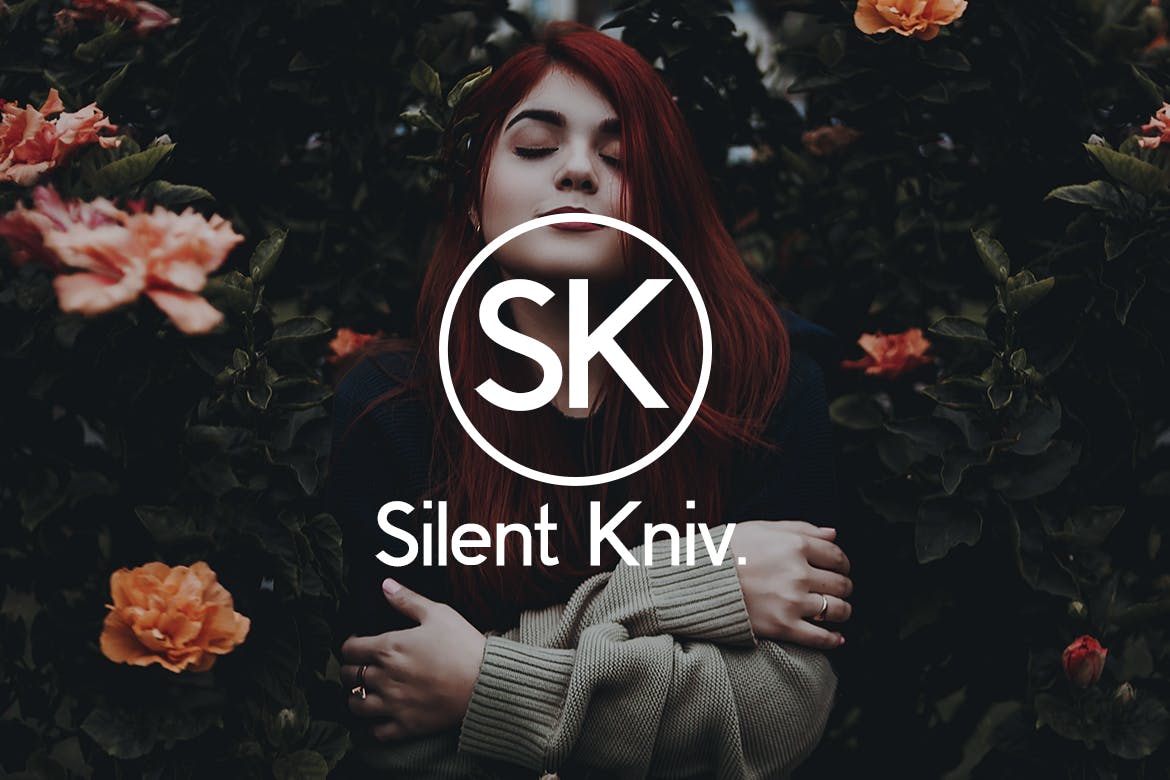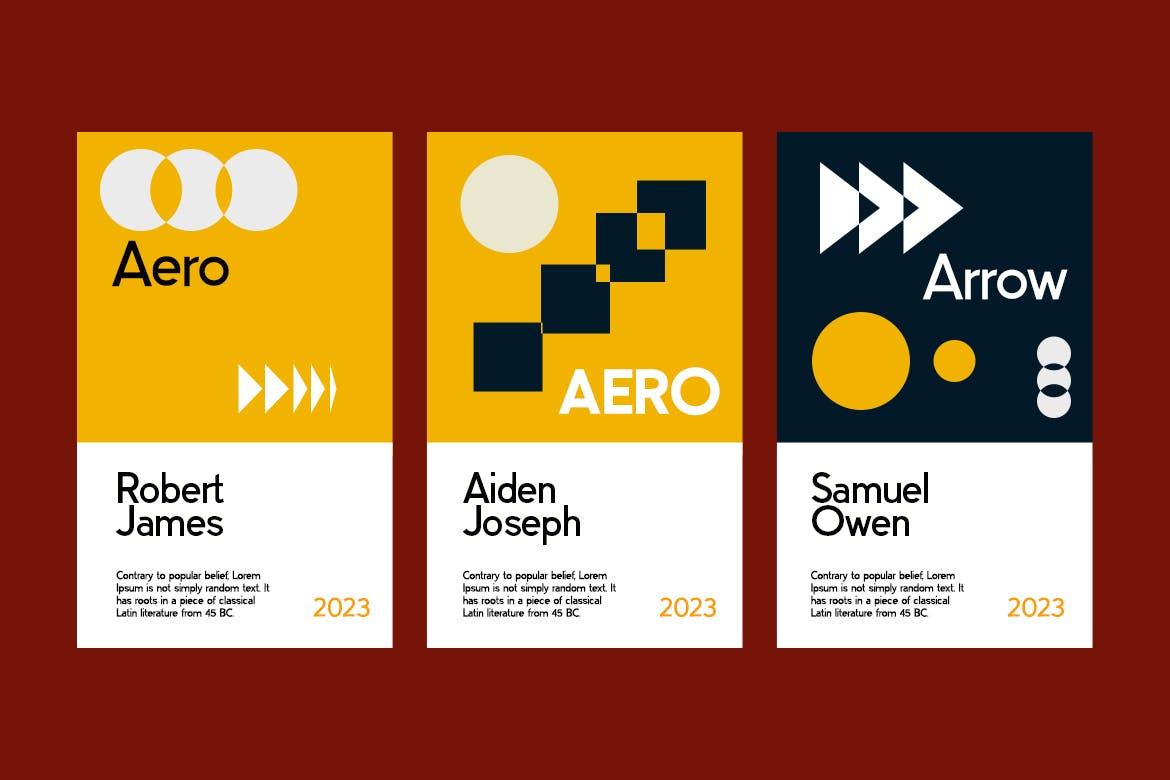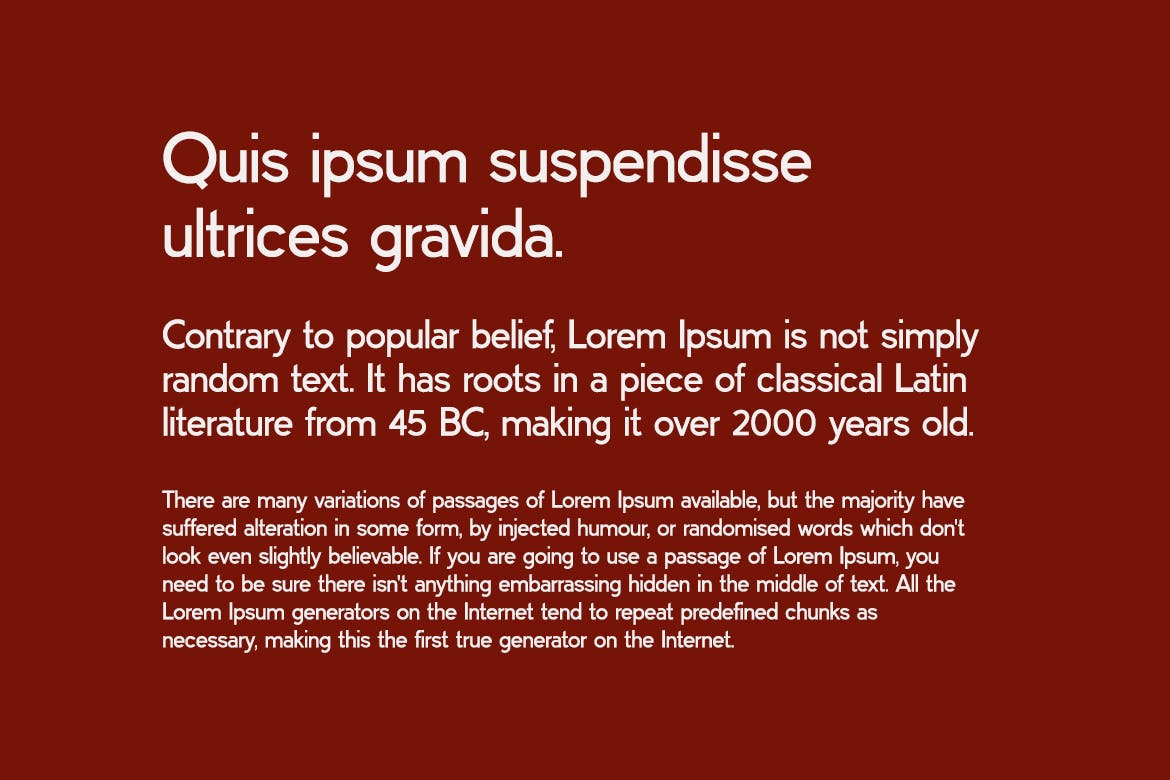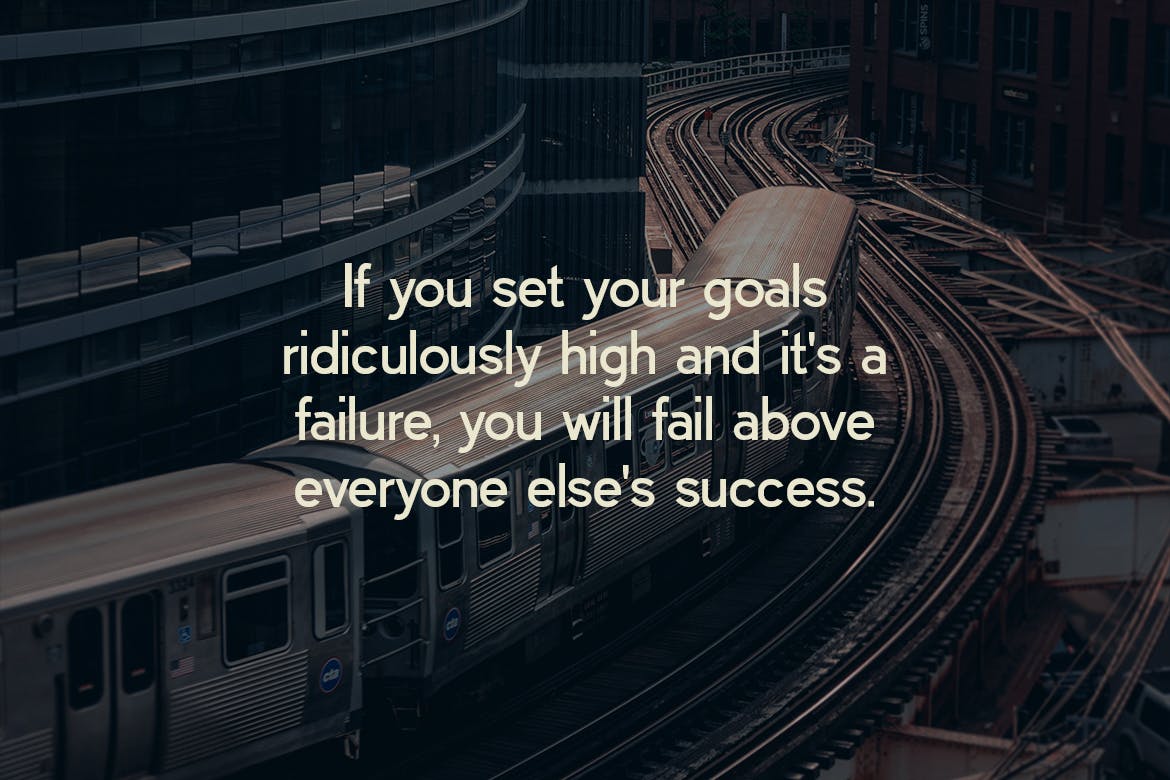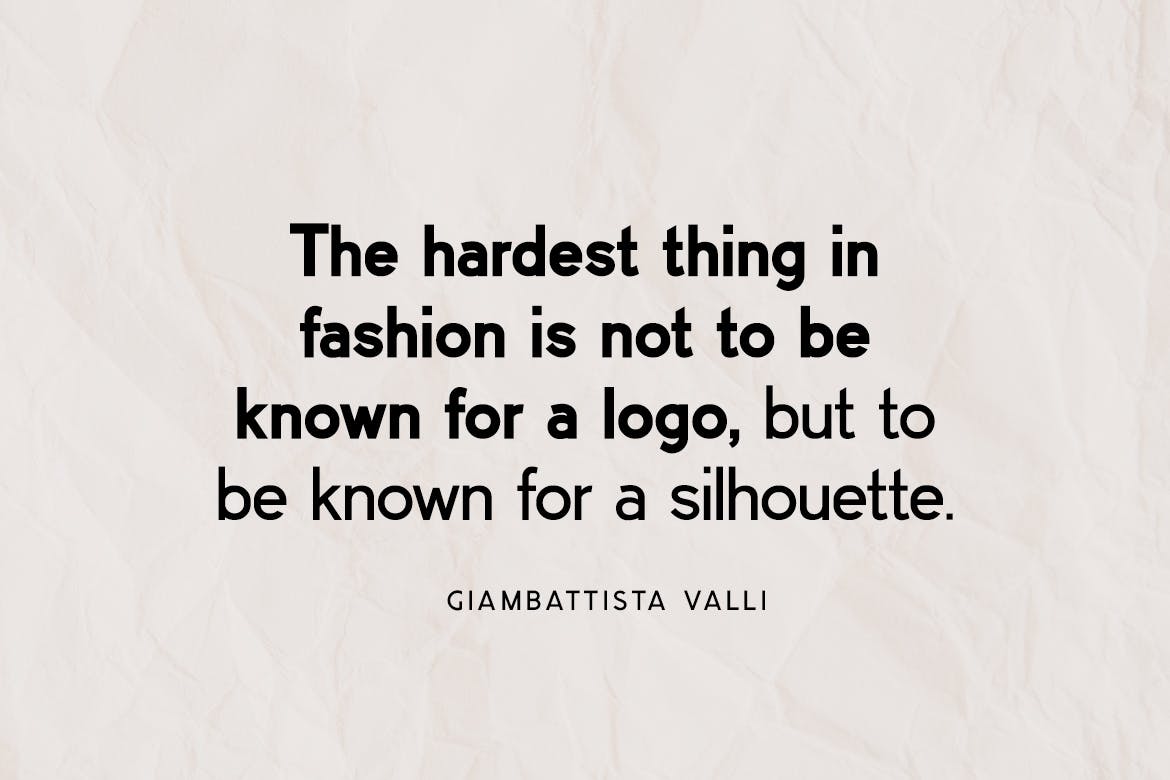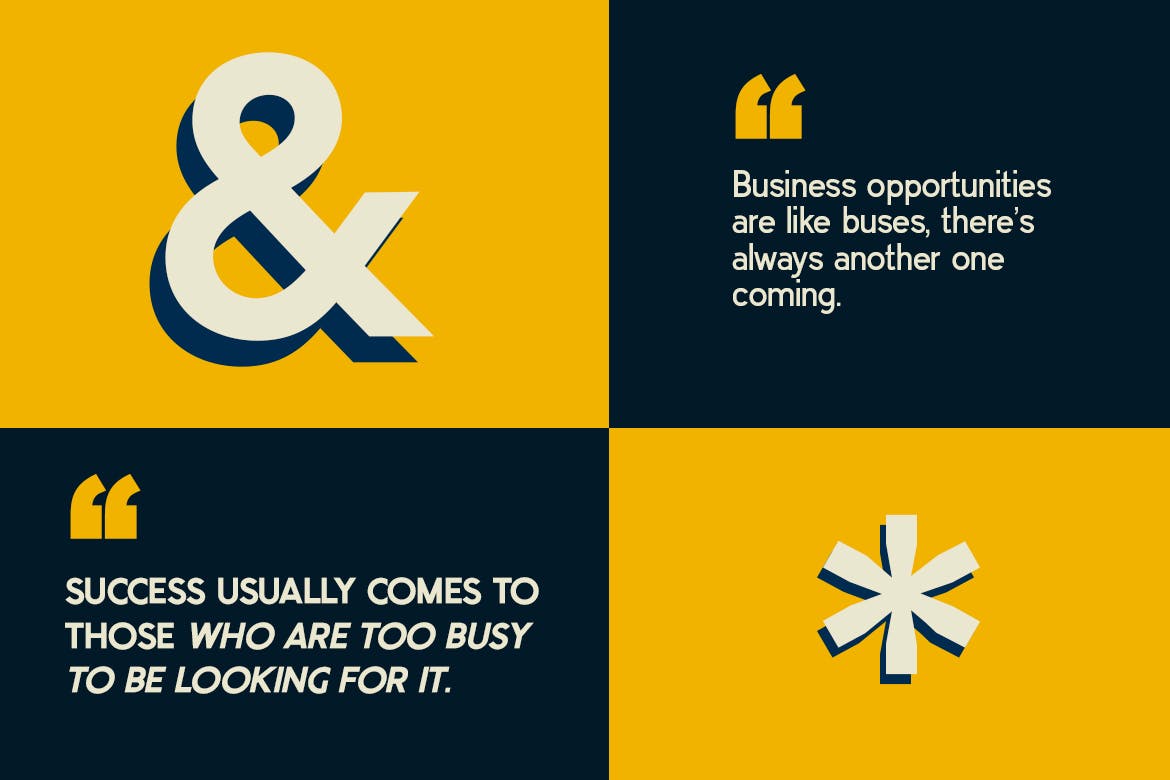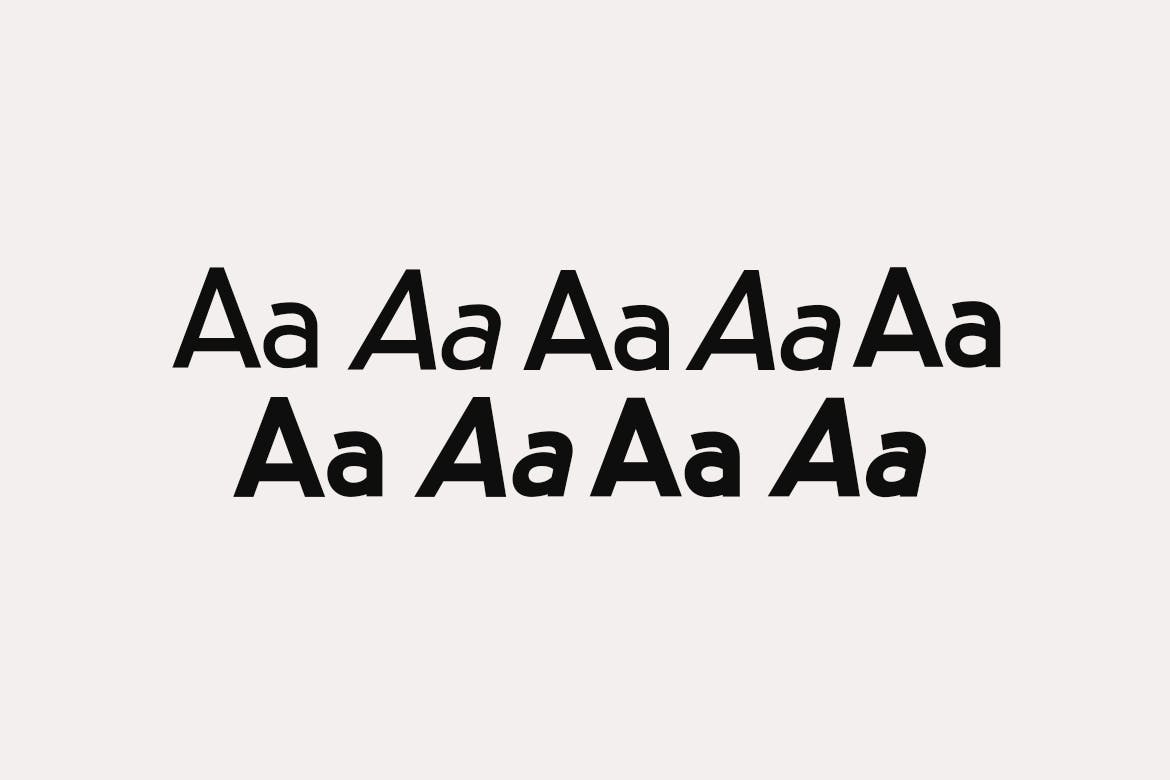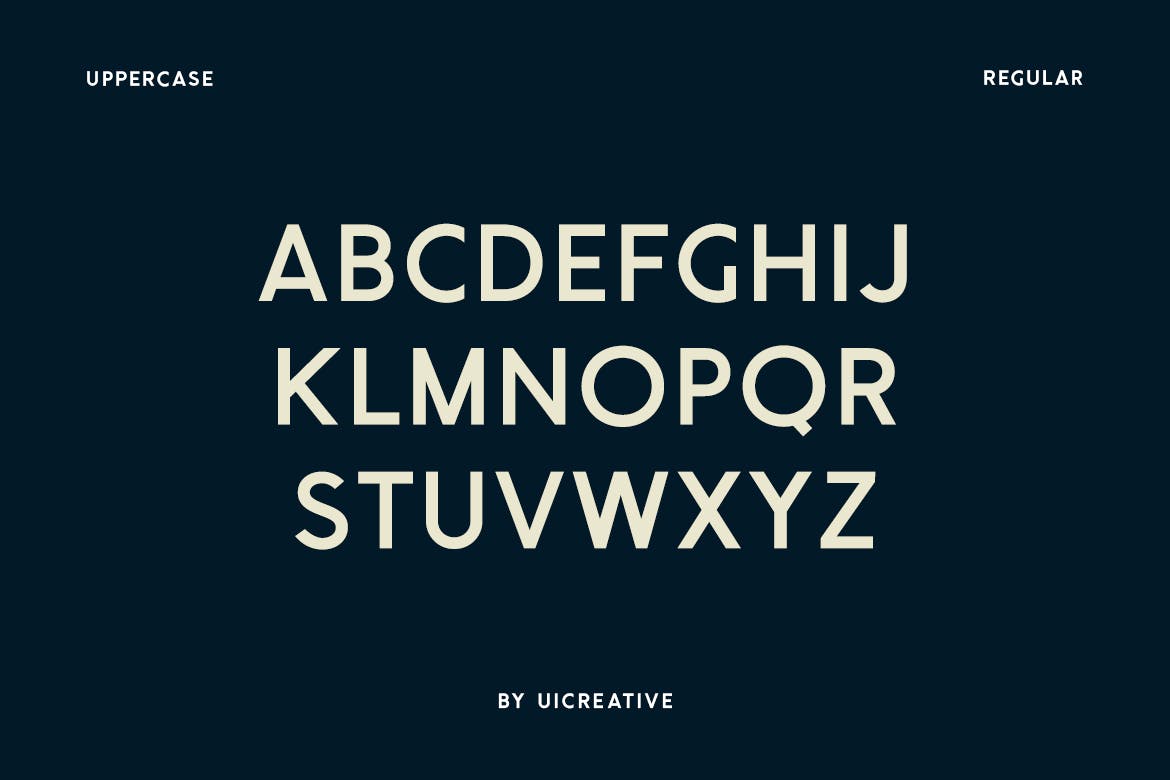
دانلود فونت Mandisa مدرن و شیک برای طراحی
Mandisa Modern Sans Serif Family Font
فونت Mandisa با طراحی مدرن و شیک، مناسب برای پروژه‌های مختلف طراحی.
به شما فونت جدید ما را معرفی می‌کنیم، فونت Mandisa مدرن Sans Serif که احساسی زیبا، کلاسیک، و مدرن دارد. این فونت به‌طور کامل برای انواع پروژه‌ها مناسب است، از جمله امضا، لوازم اداری، لوگو، طراحی عروسی، نقل قول‌های تایپوگرافی، جلد مجله یا کتاب، سرصفحه‌های وب‌سایت، برندینگ، طراحی بسته‌بندی و موارد دیگر. همچنین، طراحی برندینگ یا ویرایش مرتبط با مد، هر دو ویژگی‌های مردانه و زنانه را به نمایش می‌گذارد.